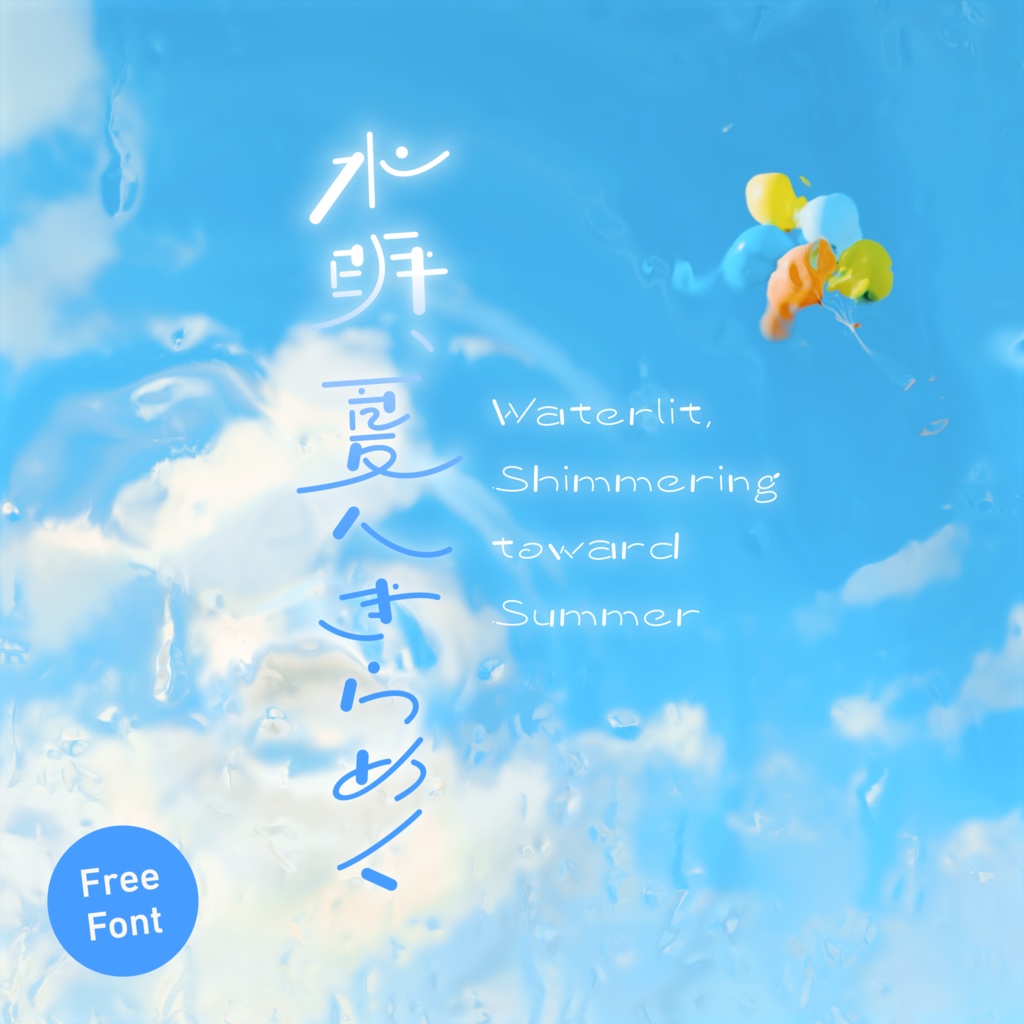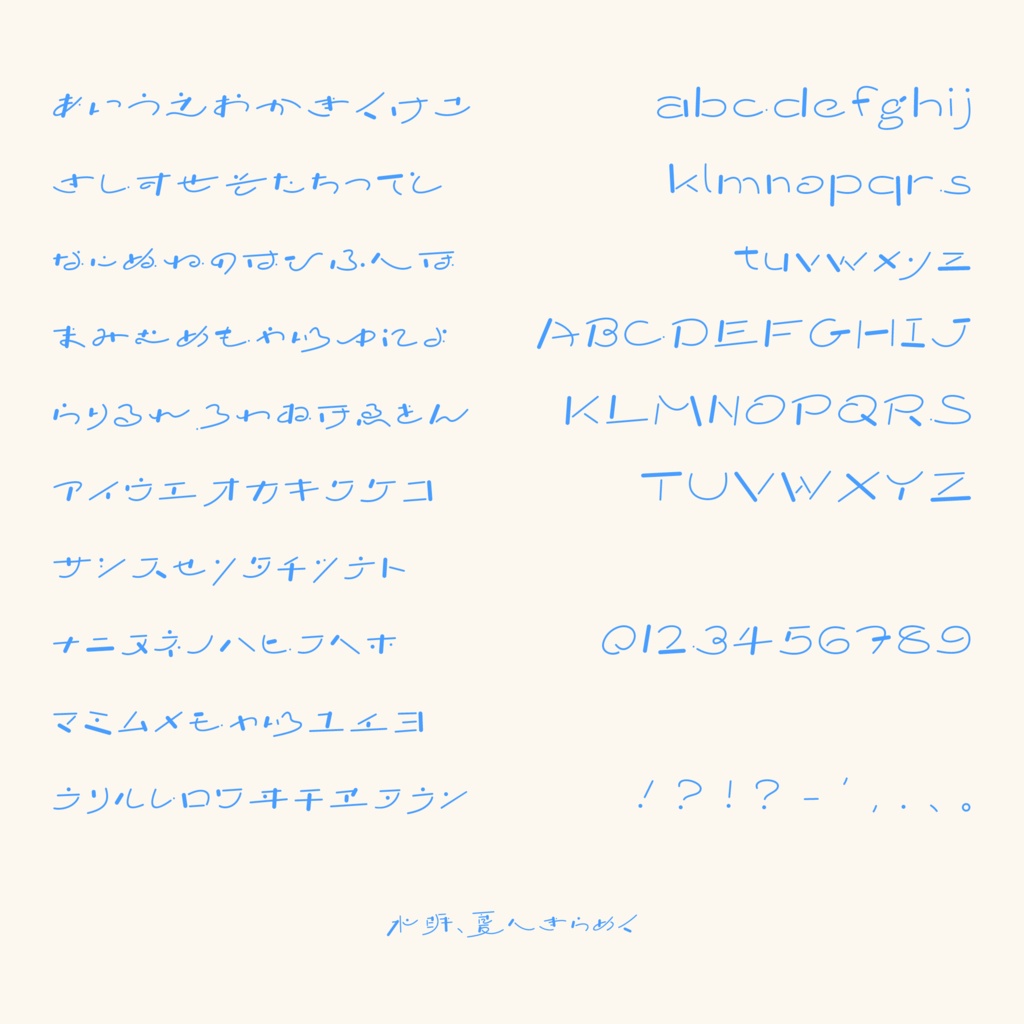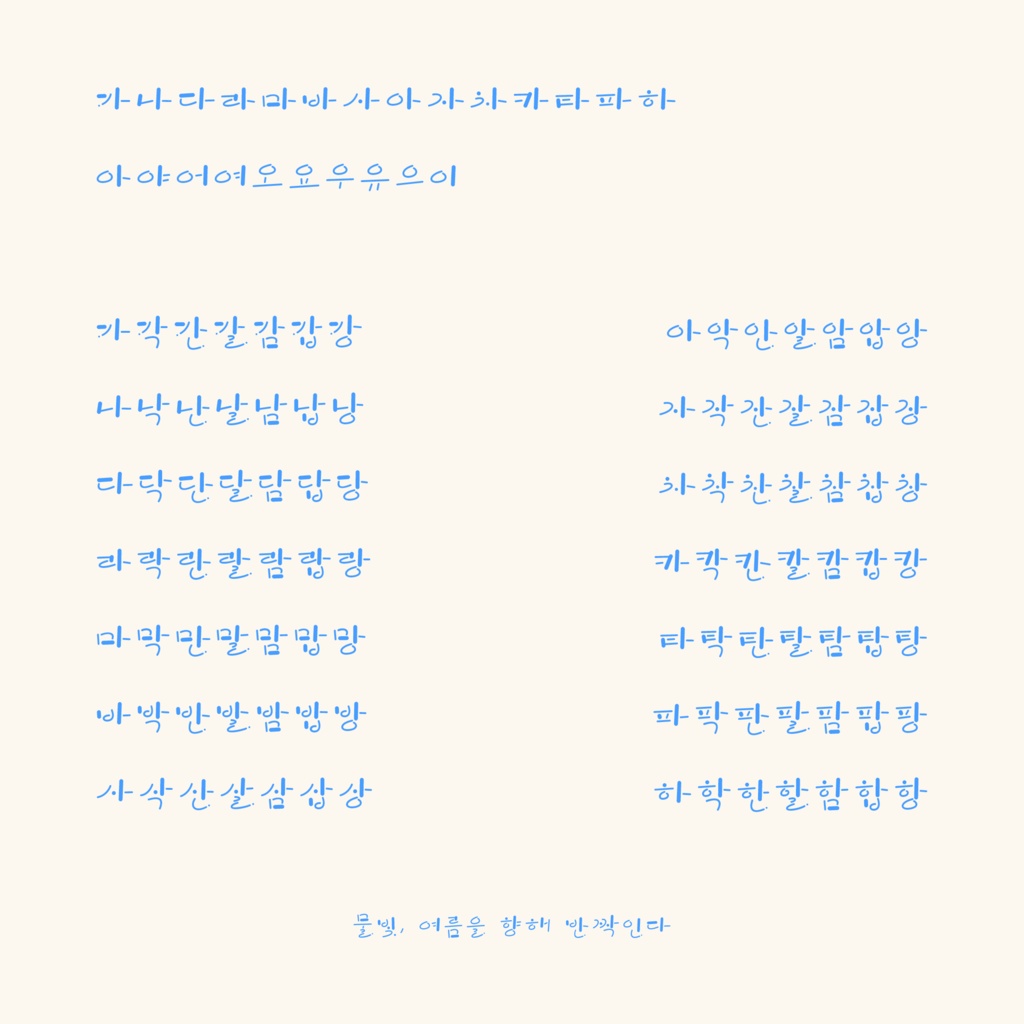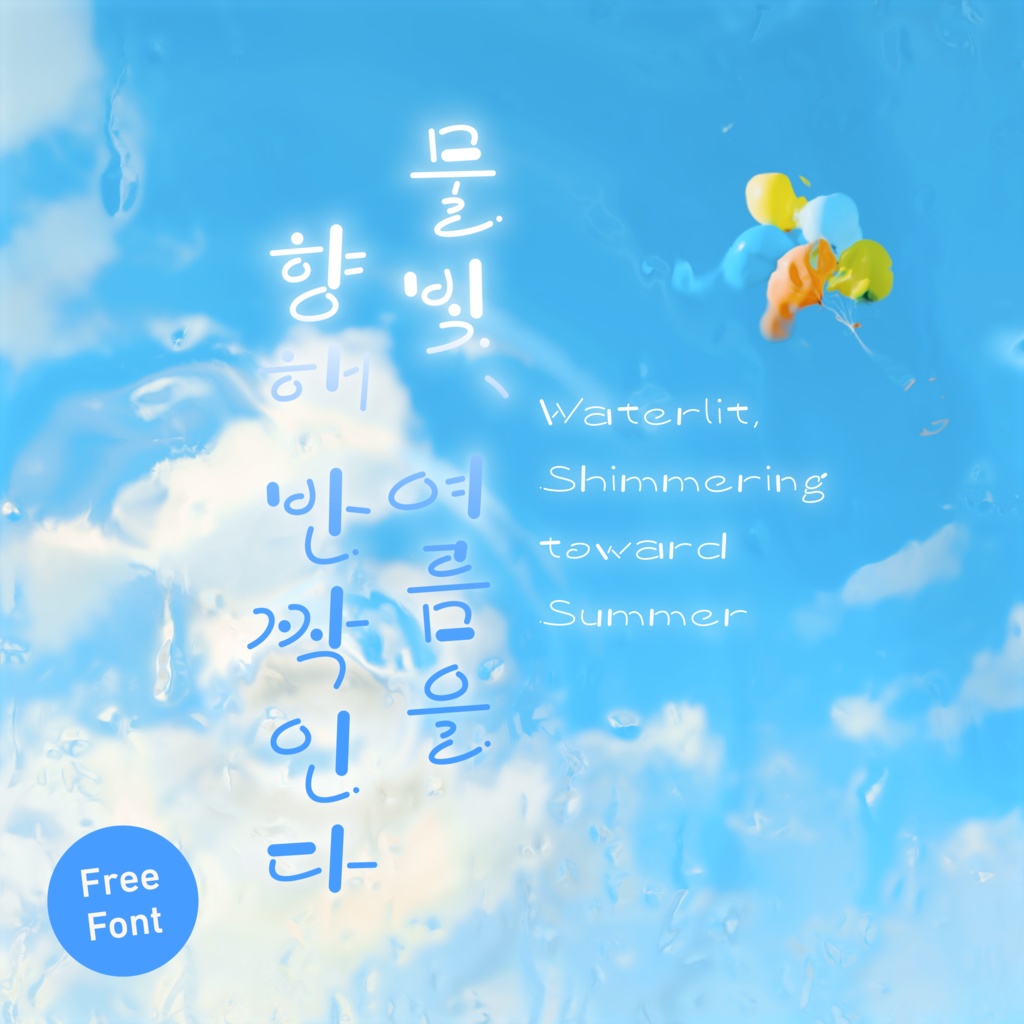
【フォント】水明、夏へきらめく【フリー版あり】
☀️🌴 SUMMER SALE 開催中!🌴☀️ \ 7/29〜8/12 23:59まで! / 通常価格:1,280円 🔥 セール価格:800円【37.5%OFF】 この夏だけのお得な価格をお見逃しなく!🍉✨ 春から初夏にかけての、きらびやかで爽やかなイメージを表現 手書きのニュアンスを活かした、軽快でポップなデザイン ※ BOOTHでは大文字とひらがなと一部の記号のみMini版と完全版を公開しています。 ●Free版の入手方法 Free版にはカタカナと小文字とハングル基本音節2,780文字が含まれています。 ・ぷらいべったー( https://privatter.net/i/7869219 )に記載のリンク先から入手できます。 ・ページの閲覧には、Xにて @PALF_MovieWorks をフォローしていただく必要がございます。 【フォント仕様】 [Mini版] ひらがな・標準ラテン文字(大文字のみ)・数字・一部記号・漢字3文字(水明夏) 234文字 / 472グリフ収録 [完全版] ひらがな・カタカナ・ASCII文字・一部記号・ハングル字母・ハングル音節文字(全音節11,172字)・漢字3文字(水明夏) 11,724文字 / 23,381グリフ収録 OpenTypeフォント / TrueTypeフォント 【利用規約】 当フォントをご利用された時点で、この利用規約に同意したものと見做します。 当フォントデータは、本規約に定める条件でご利用者様に使用する権利を許諾します。 当フォントの著作権やその他一切の権利はPalfに帰属します。 ●使用条件 1) 2人以上の複数人でご利用になる場合のみ、1ライセンスにつき端末3台までといたします。 2) 本フォントを使用して得られる結果については、仕様者自身が責任を負うものとします。 3) 一般印刷物の作成(ポスター、書籍、フライヤー等)にご利用いただけます。 4) 立体制作物の作成(ステッカー、Tシャツ、アクリルキーホルダー等)にご利用いただけます。 5) 映像及びWebに関連する制作物に於いては、画像化・アウトライン化した上でご利用いただけます。 6) ロゴマーク、タイトルデザインの作成にご利用いただけます。 7) 画像化・アウトライン化したものを加工・変形してご利用いただけます。 8) 購入者本人又は事務所内等での限定した使用に限り、当フォントファイルを改変し、本人のみが使用することができます。 ●禁止事項 当フォントファイルを使用する際、以下の事項を禁じます。 1) 第三者への譲渡・貸与・配布・販売 2) 当フォントデータを元とした、類似又は同一フォントのデータの作成 3) 公序良俗に反する目的、誹謗中傷目的での使用 4) 政治的・宗教的利用 5) 犯罪への利用 6) 当フォントのサーバー上へのアップロード 7) 当フォントデータを取り出すことができるソフトウェアへの組み込み ●その他 ・上記に記載されていない事項については、著作権法及び関連法規に従うものとします。 ・本利用規約は予告なしに変更されることがあります。
봄부터 초여름에 걸친, 화려하고 상쾌한 이미지를 표현 손글씨의 뉘앙스를 살린, 경쾌하고 팝적인 디자인 ※ BOOTH에서는 대문자와 히라가나, 일부 기호만 포함된 Mini판과 완전판을 공개하고 있습니다. ●Free판을 얻는 방법 Free판에는 가타카나와 소문자, 한글 기본 음절 2,780자가 포함되어 있습니다. ・프라이베터( https://privatter.net/i/7869219 )에 기재된 링크를 통해 얻으실 수 있습니다. ・페이지 조회를 위해서는, X에서 @PALF_MovieWorks를 팔로우해주셔야 합니다. 【폰트 사양】 [Free판] 히라가나・표준 라틴 문자(대문자만)・숫자・일부 기호・한자 3문자(水明夏) 234문자 / 472글리프 수록 [완전판] 히라가나・가타카나・ASCII 문자・일부 기호・한글 자모・한글 음절 문자(전체 음절 11,172자)・한자 3문자(水明夏) 11,724문자 / 23,381글리프 수록 OpenType 폰트 / TrueType 폰트 【이용 규약】 본 폰트를 사용한 시점에서, 이 이용 규약에 동의한 것으로 간주합니다. 본 폰트 데이터는, 본 규약에 정한 조건으로 이용자님에게 사용할 권리를 허락합니다. 본 폰트의 저작권 및 기타 일체의 권리는 Palf에게 귀속됩니다. ●사용 조건 1) 2인 이상의 다수가 사용할 경우에만, 1라이선스당 단말기 3대까지로 합니다. 2) 본 폰트를 사용하여 얻은 결과에 대해서는, 사용자 자신이 책임을 집니다. 3) 일반 인쇄물 제작(포스터, 서적, 전단지 등)에 이용하실 수 있습니다. 4) 입체 제작물 제작(스티커, T셔츠, 아크릴 키홀더 등)에 이용하실 수 있습니다. 5) 영상 및 Web과 관련된 제작물에서는, 이미지화・아웃라인화한 후에 이용하실 수 있습니다. 6) 로고 마크, 타이틀 디자인 제작에 이용하실 수 있습니다. 7) 이미지화・아웃라인화한 것을 가공・변형하여 이용하실 수 있습니다. 8) 구매자 본인 또는 사무실 내 등 제한된 사용에 한해, 본 폰트 파일을 개조하여, 본인만이 사용할 수 있습니다. ●금지 사항 본 폰트 파일을 사용할 때, 다음 사항을 금지합니다. 1) 제3자에게 양도・대여・배포・판매 2) 본 폰트 데이터를 바탕으로 한, 유사 또는 동일한 폰트 데이터 제작 3) 공서양속에 반하는 목적, 비방 중상 목적의 사용 4) 정치적・종교적 이용 5) 범죄에의 이용 6) 본 폰트를 서버 상에 업로드 7) 본 폰트 데이터를 추출할 수 있는 소프트웨어에 통합 ●기타 ・상기에 기재되지 않은 사항에 대해서는, 저작권법 및 관련 법규를 따르기로 합니다. ・본 이용 규약은 예고 없이 변경될 수 있습니다..